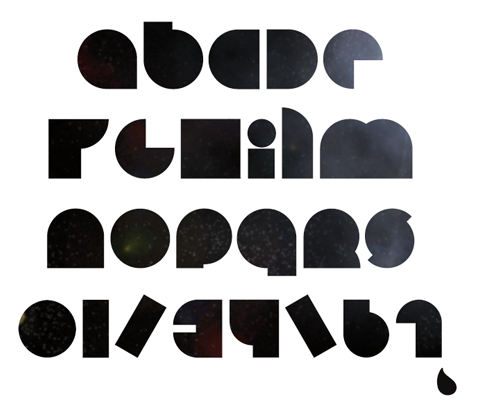
Ultraultra-black - welche ist das? Oder ne ähnliche?
Uff, das is ja ein krasses Ding.
Ähnlich bzw. ungefähr in die Richtung: (Sorry, der frisst irgendwie die Schriftmuster nicht, daher nur per Links)
Ultra Fat
Lazar
Parkitecture
Supper Club (mit Minuskeln!)
Wagner Silhouette (dito)
Aber vielleicht weiß ja jemand noch genau, was das da ist.
… ehmm … das ist aber nicht für Euern Film, oder? :shock:
Die von Nina erwähnten sind mir teilweise zu eckig. Aber von Supper Club bin ich begeistert. Und - ja! - mit Minuskeln!
Aber ich denke dass Schwalbenkoenigs Fund am ehesten an's Original rankommt. Und dazu noch Freefont, wie ich das sehe!
@Nina: Nein, nicht für den Film. Matze hat mich gefragt, ob ich "so eine" kenne.